Font serif memiliki tampilan menarik karena memiliki serif yang bervariasi dan menciptakan mood yang berbeda. Variasi serif yang kotak dan tebal pada font slab serif menciptakan kesan bold, formal dan strong. Dalam desain grafis penggunaan font slab serif memerhatikan kelebihan serta kebutuhan desain sehingga menarik dan relevan. 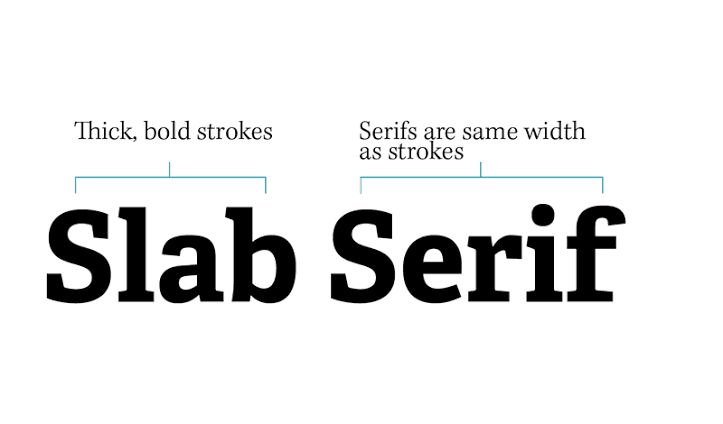
Karakteristik umum dari font slab serif dengan bentuk tebal dan kotak ini terlihat tebal, seringkali hurufnya cukup tebal. Garis huruf terlibat tebal baik pada lebar dan tinggi sehingga tampil mencolok. Umumnya font slab serif akan tampil seperti:
- Bold
- Strong
- Modern Aesthetic
Font yang tebal ini dalam penggunaannya populer untuk kebutuhan teks judul, tajuk berita, dan logo. Pemilihan font ini biasanya juga dipengaruhi karena ingin tampil berani dan mengesankan. Bentuk huruf yang tebal dan terlihat tegas akan menyampaikan pesan yang kuat dan stabil.
KELEBIHAN FONT SLAB SERIF
Font serif jenis ini dapat digunakan dalam desain grafis untuk berbagai jenis desain dan kebutuhan. Penggunaan font slab serif dapat menciptakan berbagai mood dan kesan berbeda. Pertimbangkan beberapa kelebihan ini ketika ingin menggunakan font slab serif:
Tampil Kokoh dan Tegas
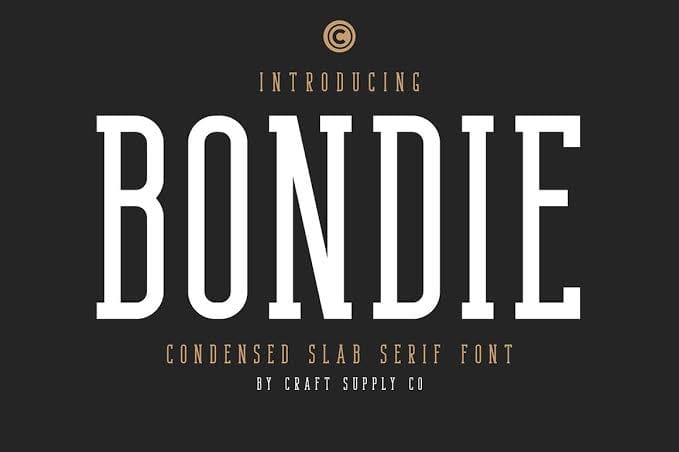
Font ini memiliki bentuk huruf yang tebal dan tegas, serta gaya serif kotak sehingga menciptakan kesan kokoh dan tegas. Pada desain logo, font ini akan efektif mencerminkan brand yang tegas, formal dan strong. Penggunaan font ini bisa mencerminkan identitas visual untuk logo perusahaan atau logo organisasi olahraga.
Seringkali font slab serif digunakan dalam variasi font tebal sehingga bentuknya semakin kokoh dan tegas. Gaya font ini juga akan efektif mencerminkan tema desain poster untuk sport. Beberapa jenis slab serif memiliki gaya huruf yang geometris sehingga tampil semakin kokoh.
Mudah Dibaca
Gaya font slab serif juga dipilih karena memiliki kelebihan untuk dibaca karena bentuk huruf yang bersih dan sederhana. Bentuk sertifnya mungkin kotak tetapi garis hurufnya bersih sehingga mudah untuk dibaca. Selama font digunakan pada ukuran yang tepat maka teks akan mudah dibaca.
Pada desain logo, poster hingga banner font slab serif akan mudah terbaca, ukuran yang besar akan semakin mudah dibaca. Untuk digunakan pada teks yang berukuran kecil pastikan untuk mengatur ketebalan yang sesuai. Penggunaan teks dengan font slab serif akan tampil menarik dan mudah dibaca sehingga bisa digunakan untuk berbagai kebutuhan.
Versatile atau Mudah Digunakan
Font ini juga dapat digunakan untuk berbagai jenis desain seperti logo, judul poster, hingga desain kemasan. Kemampuan font untuk beradaptasi dalam berbagai desain ini membuat relevan hingga saat ini. Berbagai variasi gaya huruf membuatnya mudah digunakan pada berbagai jenis desain dan berbagai ukuran teks.
Namun pastikan font slab serif sesuai dengan tujuan atau tema sehingga tampil harmonis. Untuk dikombinasikan pada jenis desain yang memiliki banyak teks, pilih jenis font yang lebih sederhana seperti sans serif yang tidak memiliki serif. Font ini juga bisa digunakan untuk menciptakan hirarki visual dengan menggunakan nama merek.
Mencerminkan Kesan Tradisional atau Vintage
Gaya desain yang bertema vintage atau retro juga bisa menggunakan font slab serif yang bergaya klasik. Bentuk serif kotak menciptakan gaya huruf yang tampak formal dan seperti font pada era klasik. Gaya font ini sudah cukup populer sejak lama sehingga bisa digunakan untuk merepresentasikan tema desain vintage.
Dalam desain logo barbershop yang bergaya vintage penggunaan font slab serif cukup populer. Pada desain poster atau kemasan yang bertema vintage font ini akan tampil harmonis dan menciptakan nostalgia. Jenis font ini bisa menciptakan kesan vintage yang mana seringkali ditambahi tekstur grainy dan garis outline.
Variasi Gaya
Font slab serif ini juga memiliki kelebihan dalam penggunaan untuk berbagai kebutuhan tema dan jenis desain. Hal ini karena font ini memiliki berbagai variasi gaya yang bisa menciptakan mood dan kesan yang berbeda-beda. Variasi gaya font slab serif ini memiliki gaya modern, geometris hingga vintage.
Bahkan banyak juga variasi slab serif yang lebih dekoratif sehingga menciptakan tampilan yang unik dan fleksibel untuk berbagai tema. Banyaknya variasi gaya slab serif ini membuat font akan mudah digunakan untuk mencerminkan berbagai tema dan pesan. Variasi gaya font slab serif akan membantu font menciptakan desain visual yang menarik tak hanya berkesan vintage.
KEKURANGAN FONT SLAB SERIF
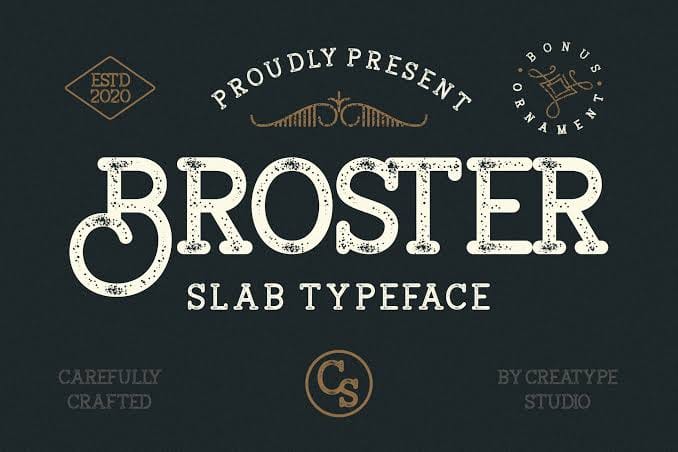
Selain memiliki kelebihan dalam menciptakan kesan vintage, tegas dan bold, perhatikan juga kekurangan dari font slab serif. Hal ini bertujuan agar font slab serif salat digunakan dengan efektif dan relevan. Berikut beberapa kekurangan font slab serif:
Sulit Dibaca Pada Ukuran Kecil dan Salah teks Panjang
Teks dalam desain grafis yang menggunakan font slab serif terkadang bisa sulit dibaca jika digunakan pada ukuran terlalu kecil. Hal ini karena adanya serif kotak dan huruf yang tebal sehingga membuat huruf ukuran sulit dibaca. Untuk itu penggunaan font slab serif disarankan untuk teks yang berukuran besar atau sedang, jangan terlalu kecil.
Font ini juga sulit dibaca pada teks yang panjang sehingga kebanyakan digunakan untuk font judul atau teks yang pendek. Teks yang panjang seperti paragraf akan sulit dibaca jika menggunakan font slab serif. Detail gaya huruf dan serifnya yang tebal akan membuat teks yang panjang terlihat terlalu rapat sehingga sulit dibaca.
Terlihat Kuno
Gaya huruf serif memang agak kuno terutama slab serif sehingga tidak cocok untuk mencerminkan kesan modern. Pada jenis desain modern, penggunaan font ini akan kurang cocok. Meski ada jenis slab serif yang modern, gaya huruf serif cenderung mulai ditinggalkan. Banyak yang lebih suka dengan gaya sans serif sehingga penggunaan slab serif menjadi cukup jarang ditemui pada era modern.
Konteks Penggunaan Terbatas
Bentuk serif kotak dan huruf tebal membuat slab serif tampil tegas dan klasik, yang mana bentuk yang unik tidak cocok untuk semua jenis desain atau brand. Penggunaan font ini cukup terbatas tidak bisa digunakan untuk semua jenis industri dan jenis brand. Hanya beberapa brand saja yang cocok dengan font slab serif seperti barbershop, logo sport, dan produk tradisional.
Slab serif hanya cocok untuk menciptakan kesan formal dan tegas, pada jenis tema yang bersih dan minimalis akan kurang cocok. Mood yang diciptakan font ini juga cukup terbatas seperti vintage dan tegas. Beberapa brand yang ingin tampil ekspresif, ramah dan alami tidak cocok dengan font slab serif.
Baca juga: Kelebihan Font Serif untuk Berbagai Desain Grafis
Terlalu Dominan
Meski memiliki kelebihan menciptakan kesan tegas dan bold, ini juga bisa menjadi kekurangan. Font slab serif dalam beberapa penggunaan bisa tampil terlalu dominan karena bold, tegas dan memiliki bentuk geometris. Hal ini akan membuat teks menjadi terlalu dominan dan mengalihkan perhatian dari elemen lain.
Alangkah baiknya font ini digunakan untuk font judul sehingga sesuai untuk menarik perhatian. Sebagai font teks sub judul atau informasi lainnya, gaya huruf bisa membuat fokus utama menjadi teralihkan.
Keterbatasan Nuansa
Font slab serif juga memiliki kekurangan dalam menciptakan nuansa atau mood sehingga tidak cocok untuk semua kebutuhan. Nuansa yang diciptakan font slab serif ini cukup terbatas seperti kesan formal, tegas dan kuat. Pada jenis nuansa brand yang elegan, feminim dan ramah tidak bisa menggunakan font slab serif.
Dalam menggunakan font slab serif yang tebal dan memiliki serif kotak ini sebaiknya untuk mencerminkan brand yang tegas, formal dan vintage. Kemampuan font tersebut akan membuat brand tampil menarik dan relevan. Pertimbangkan kelebihan dan kekurangan dari gaya font slab serif untuk digunakan dalam desain grafis agar relevan. Pastikan font slab serif digunakan untuk desain logo, kemasan dan poster dengan tema dan style yang relevan.